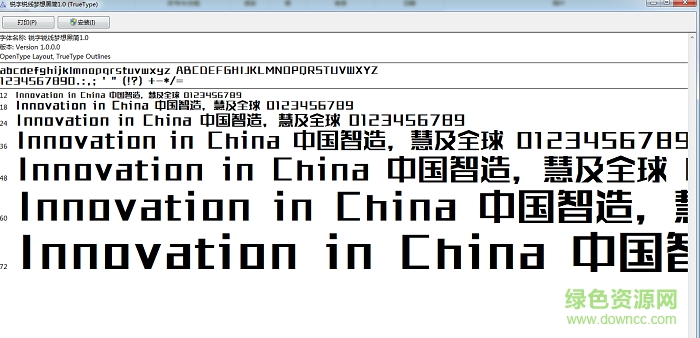
bigruixianboldkgbv1.0 字體
bigruixianboldkgbv1.0字體又叫銳字銳線夢想黑簡1.0字體,字體呈方形,外形堅實工整,蒼勁有力,卡通設(shè)計、包裝設(shè)計、影視設(shè)計都用得到,喜歡高顏值字體的朋友快來綠色資源網(wǎng)下載吧!
bigruixianboldkgbv1.0字體特點
字體清秀工整,結(jié)構(gòu)均勻,匠心獨具,印刷效果清晰明快,可用于文章標題、廣告制作、裝飾裝幀等。